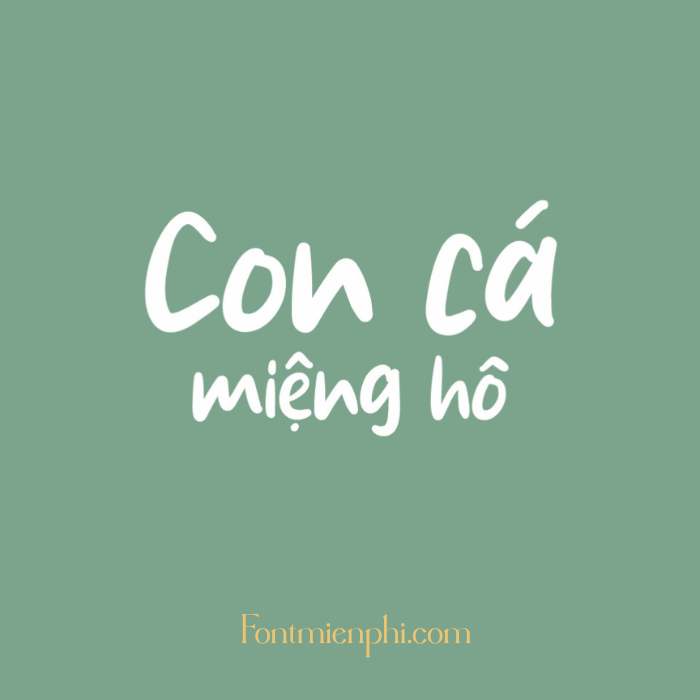
Font Việt hóa 1FTV VIP Original Fish
• Tác giả:  MJType
Giới thiệu về bộ Font Việt hóa 1FTV VIP Original Fish
Trong thế giới đồ họa hiện đại, việc tìm kiếm một bộ font vừa mang tính nghệ thuật vừa dễ sử dụng là ưu tiên hàng đầu. Font Việt hóa 1FTV VIP Original Fish chính là lựa chọn hoàn hảo cho những ai yêu thích phong cách tự nhiên và mềm mại. Đây là một phông chữ được thiết kế dựa trên cảm hứng từ những đường nét uyển chuyển của sinh vật biển, mang lại cảm giác phóng khoáng và tràn đầy năng lượng. Khi sử dụng Font Miễn Phí này, các bạn học sinh và thầy cô có thể dễ dàng tạo ra những slide bài giảng hay tờ rơi sự kiện trường học vô cùng bắt mắt. Phiên bản Việt hóa giúp loại bỏ hoàn toàn lỗi hiển thị dấu tiếng Việt, đảm bảo tính thẩm mỹ cao nhất.
Ưu điểm nổi bật của phông chữ
Bộ Font Việt hóa 1FTV VIP Original Fish sở hữu các đường nét thanh mảnh nhưng không kém phần chắc chắn. Phông chữ này cực kỳ phù hợp cho các thiết kế tiêu đề, bìa sách hoặc các dự án sáng tạo cá nhân. Đặc biệt, các ký tự được tối ưu hóa để hiển thị rõ nét trên cả màn hình kỹ thuật số lẫn bản in giấy.
Cách ứng dụng Font Việt hóa 1FTV VIP Original Fish trong học tập
Đối với môi trường giáo dục, việc sử dụng Font Việt hóa 1FTV VIP Original Fish giúp bài học trở nên sinh động hơn. Thầy cô có thể dùng phông chữ này để thiết kế bảng tên lớp, thiệp chúc mừng hoặc các tài liệu trực quan sinh động. Sự độc đáo của bộ font sẽ khơi gợi cảm hứng sáng tạo cho học sinh, giúp các em hào hứng hơn trong việc trình bày báo cáo hoặc làm báo tường. Đừng ngần ngại trải nghiệm ngay để thấy sự khác biệt mà nó mang lại cho dự án của bạn.
Kết luận về bộ phông chữ Fish độc đáo